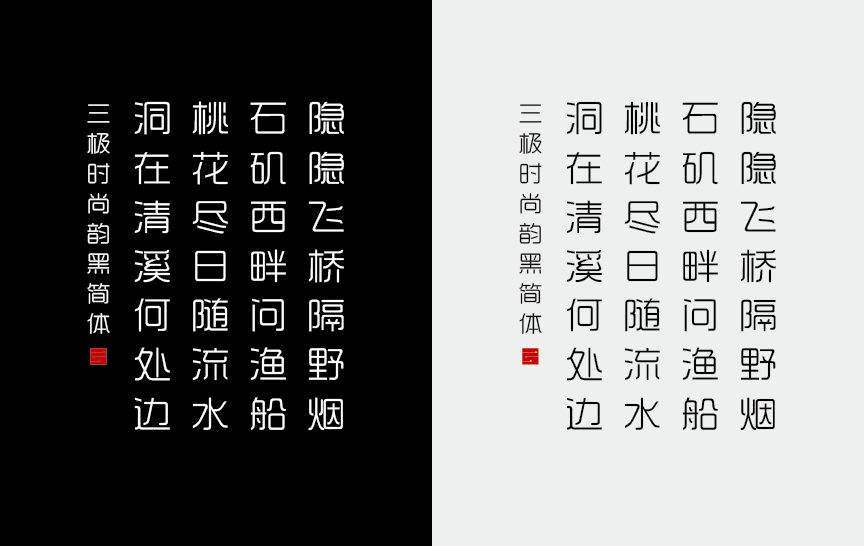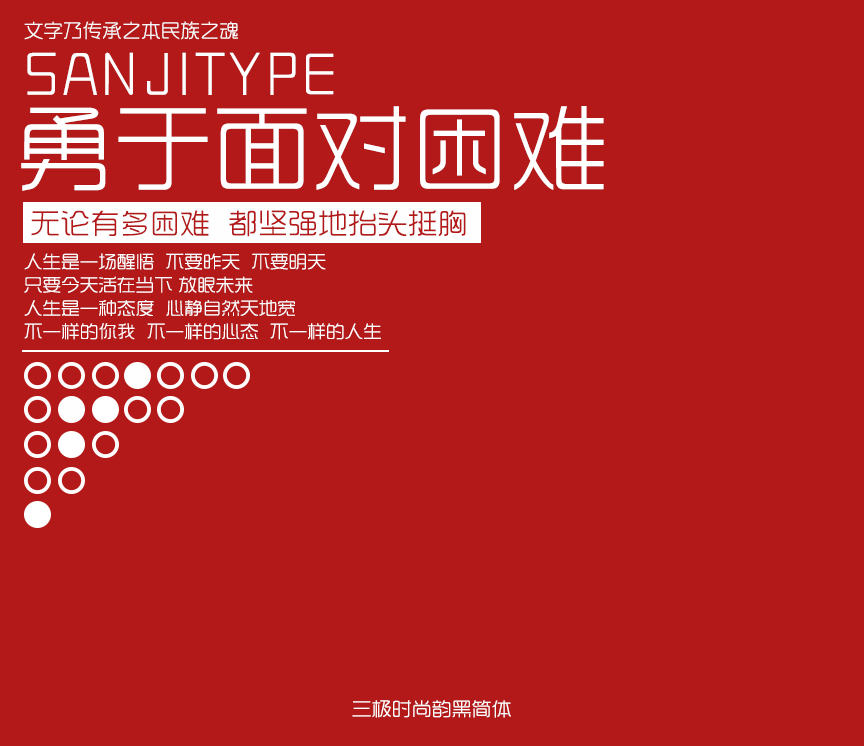
字体名称:三极时尚简体
设计师:张颖婕 何逸惠 何嘉乐
三极时尚简体字型结构优雅清秀。运笔圆润彰显秀丽,横、竖粗细一致,特点明显。大胆创意,字形稳定坚实,个性刚中带柔,易读性强。不但适用于时尚潮流类品牌广告和产品包装设计,还能胜任短文本排版。
适用媒介:杂志、书籍、广告、标志、宣传册、包装、影视、动漫、游戏,屏幕显示、交互设计。